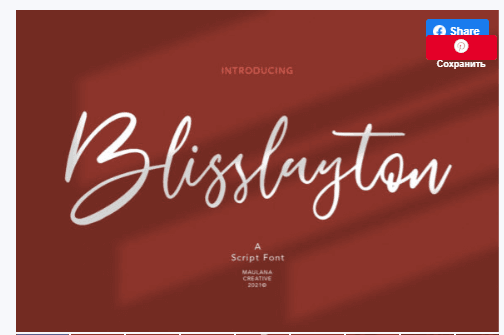
Blisslayton Font
Blisslayton - красивый, стильный и аккуратный рукописный шрифт. Он придаст изюминку любому дизайнерскому проекту, который вы желаете создать! Влюбитесь в его невероятно универсальный стиль и используйте его для создания впечатляющих дизайнов!